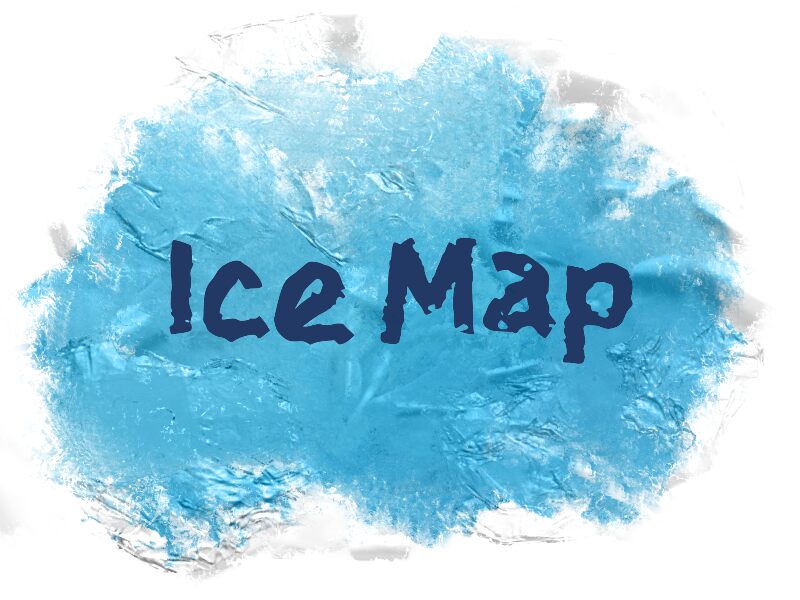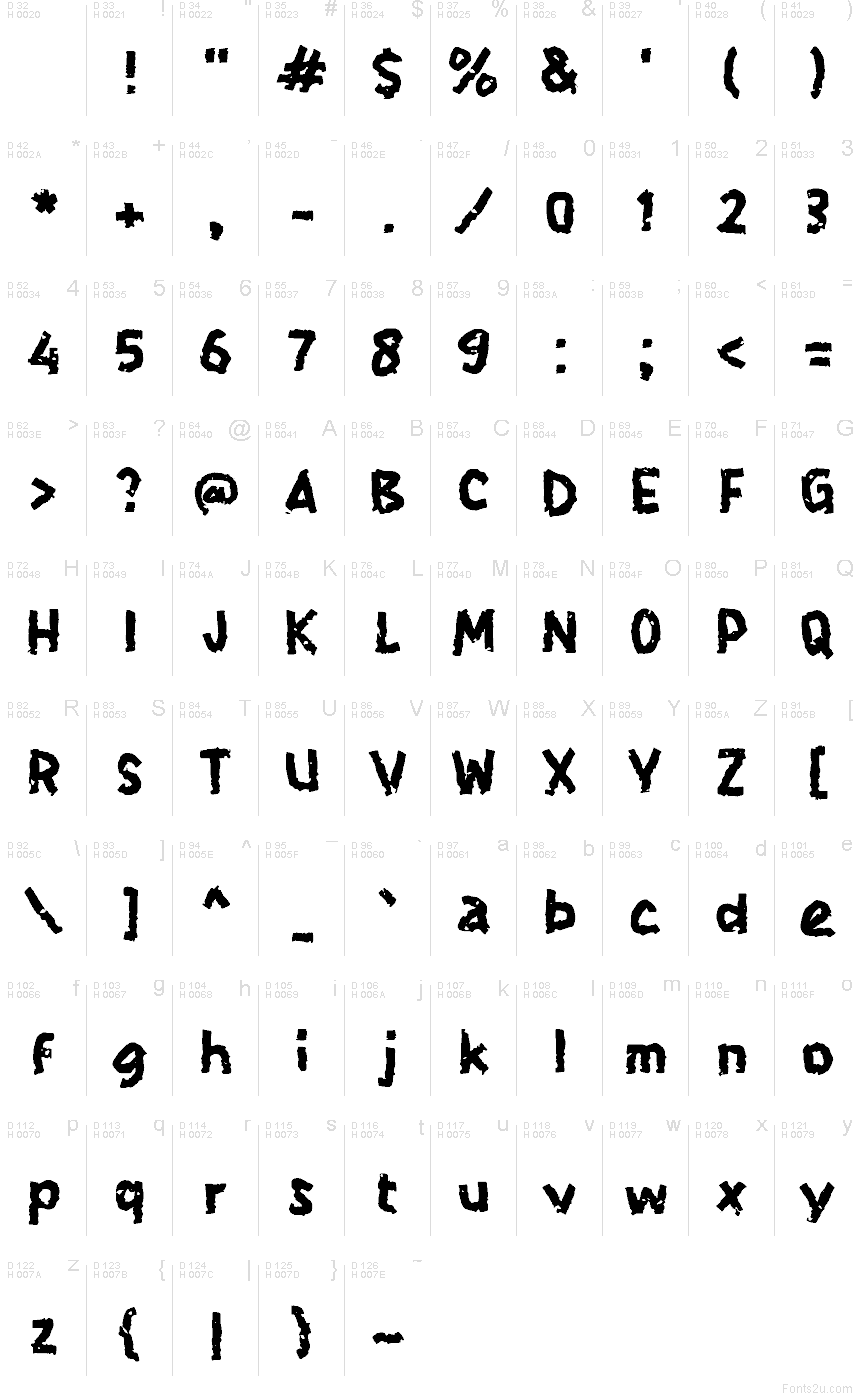
Ice Map di Wep è un font display gratuito e distorto, caratterizzato da un look grezzo, come se fosse scolpito nel ghiaccio. Le lettere non sono levigate, ma sembrano tagliate e consumate dagli agenti atmosferici, con bordi irregolari, spessori variabili e forme morbide che si sciolgono, conferendo al font un aspetto crudo e un po' ribelle.
È ideale ovunque serva un tocco ruvido e invernale per i titoli: poster, loghi per giochi indie, copertine di fanzine, volantini per eventi e scritte brevi su packaging. Grazie alla natura robusta e irregolare dei suoi glifi, rende al meglio in contesti display sintetici, come titoli di copertina, cartelli o marchi composti da una sola parola, dove l'atmosfera gelida e artigianale può davvero risaltare.
Ice Map